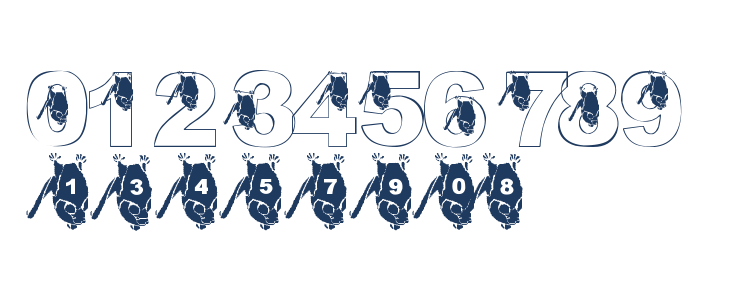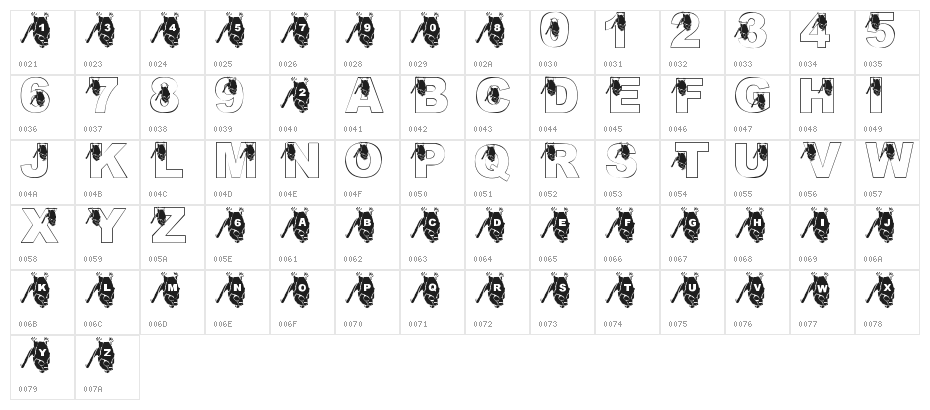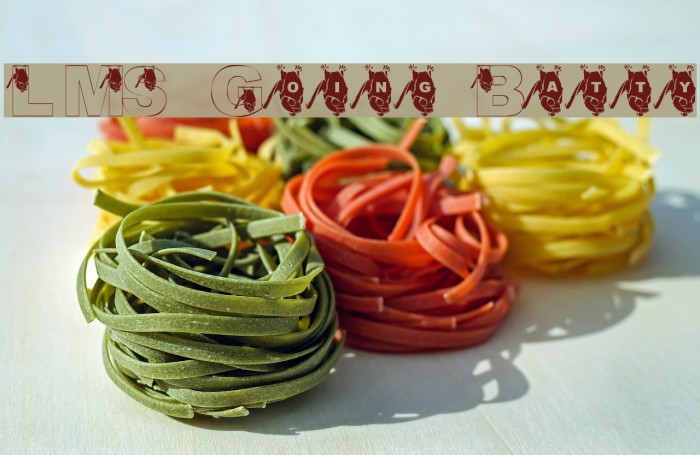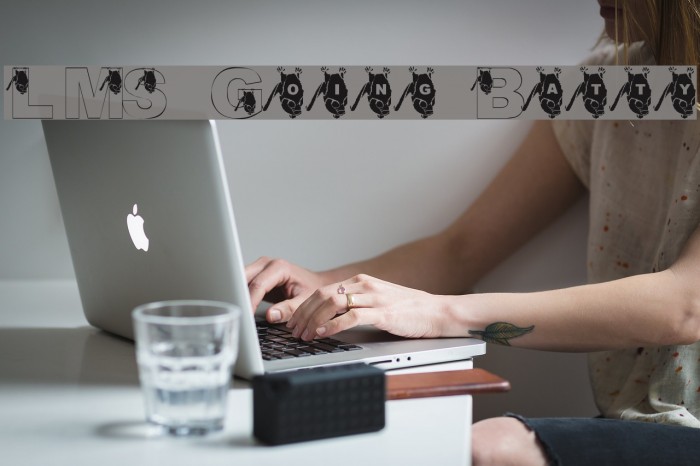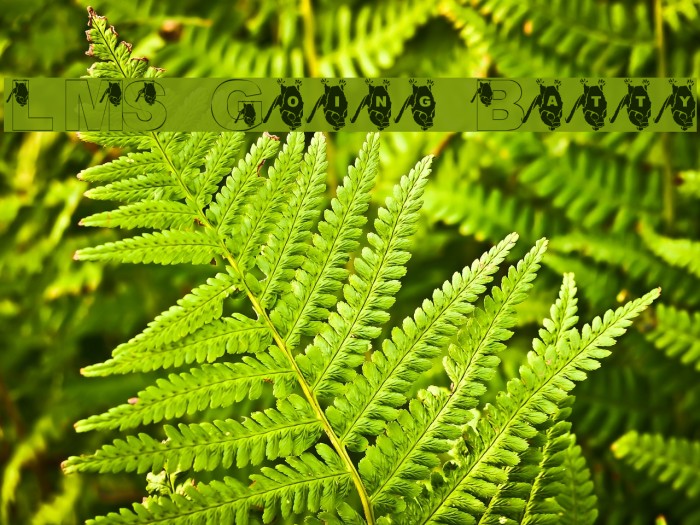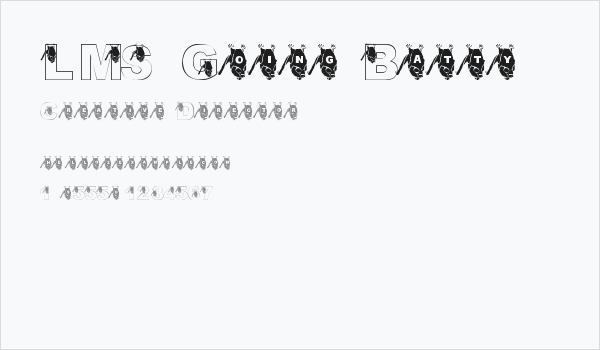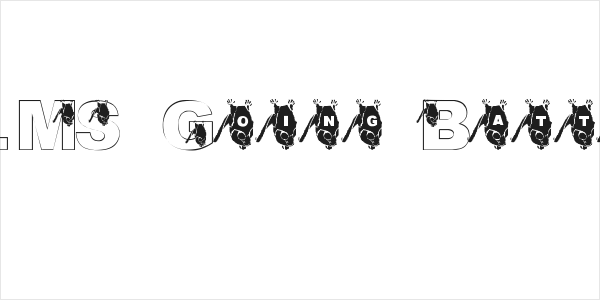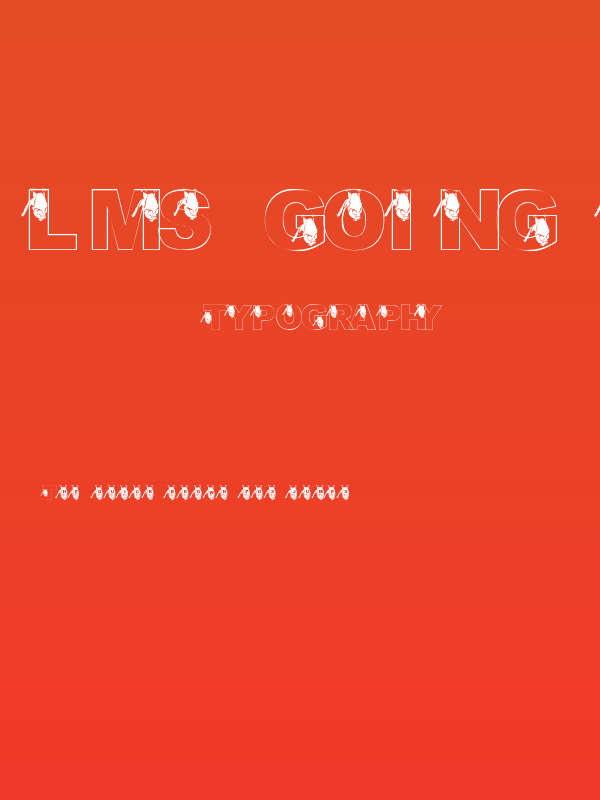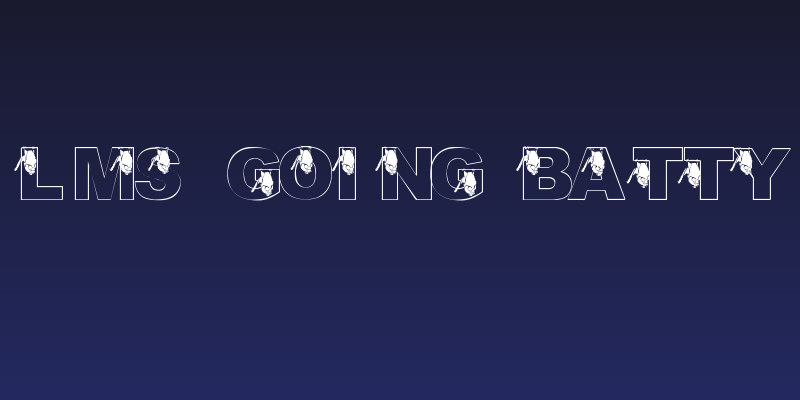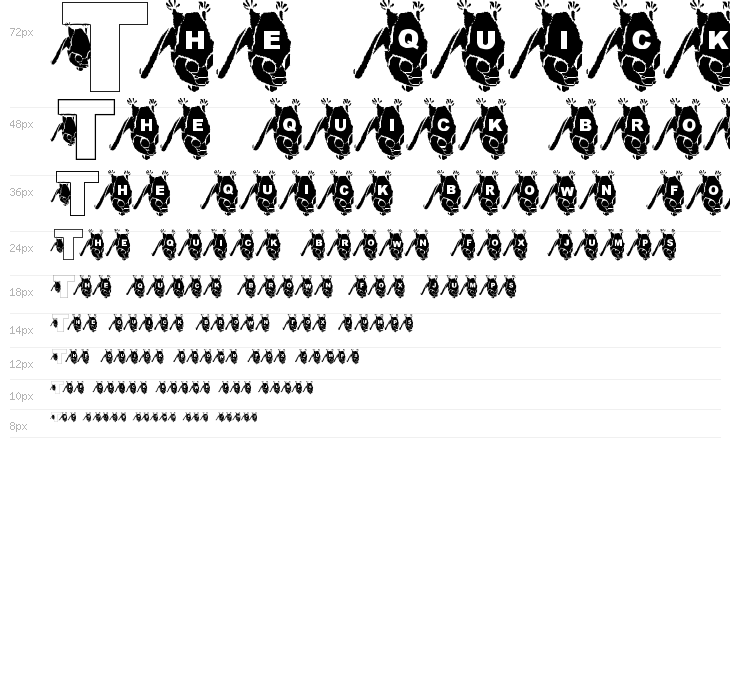
LMS Going Batty Font
| Caso d'uso | Headlines, Logos, Themed Events |
| Progetti proposti | Ideal for Halloween invitations, themed party decorations, children's book covers, and playful branding. |